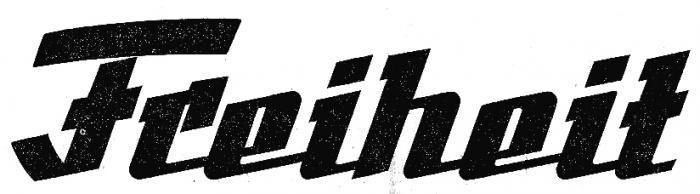
Schrift Zeitungskopf »Freiheit« (DDR-Tageszeitung) gesucht
Weiß jemand, ob der Zeitungskopf der »Freiheit« (DDR-Tageszeitung aus dem Bezirk Halle) als Satzschrift exististierte oder war das gezeichnet?
Oder kennt jemand einen ähnliche Schriftart, die da heran kommt?
Wenn ich mir das genau betrachte, dann ist das gezeichnet. Sehr sauber zwar, aber bei genauestem Vergleich interscheiden sich die beiden e und i minimal
Erinnert mich irgendwie an den Trabant-Schriftzug, ohne diesen nun genau vor Augen zu haben ... aber ich vermute auch: gezeichnet. Eine (Blei)-Satzschrift war das meines Wissens nicht. Auch wenn es sicher ne ganze Weile in den 50ern sehr modern war, so zu schreiben.
Vielleicht wäre eine Anfrage an den Nachfolger Mitteldeutsche Zeitung erfolgversprechend …
Na, damit sind wir dann ja wieder bei einem Objekt für Schriftenerkennung angelangt - aber auch bei einem Thema aus einem anderen Strang, nämlich der Frage: ist ſs in „Fleiſse“ hier richtig?